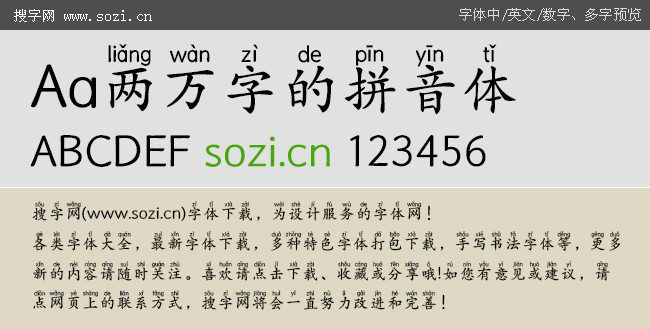
Aa兩萬(wàn)字的拼音體
搜字網(wǎng)給大家提供一款A(yù)a兩萬(wàn)字的拼音體中文字體下載,這是一款帶有拼音標(biāo)注的楷體字體,字體端正大方,適合兒童畫(huà)冊(cè)、幼兒書(shū)籍等設(shè)計(jì)應(yīng)用(此字體為個(gè)人非商用版,如需商用請(qǐng)聯(lián)系作者購(gòu)買(mǎi)版權(quán))。